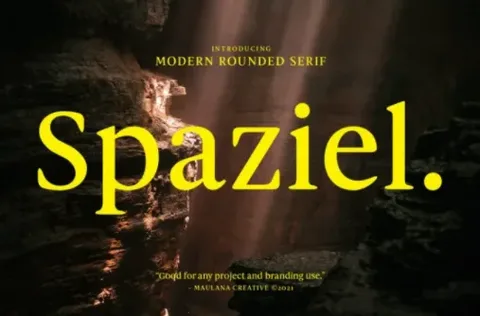
Название: Spaziel Font (2021)
Spaziel Round serif - современный шрифт с засечками. С регулярным круглым начертанием и веселым характером. Это придаст вам дополнительную креативность. Шрифт Spaziel поддерживает более 100+ языков. Этот шрифт хорошо подходит для дизайна логотипов, социальных сетей, названий фильмов, книг, короткого текста и даже длинного письма, а также для вторичного текста. Сделайте потрясающую работу со шрифтом Spaziel.
Название: Spaziel Font (2021)
Spaziel Round serif - современный шрифт с засечками. С регулярным круглым начертанием и веселым характером. Это придаст вам дополнительную креативность. Шрифт Spaziel поддерживает более 100+ языков. Этот шрифт хорошо подходит для дизайна логотипов, социальных сетей, названий фильмов, книг, короткого текста и даже длинного письма, а также для вторичного текста. Сделайте потрясающую работу со шрифтом Spaziel.